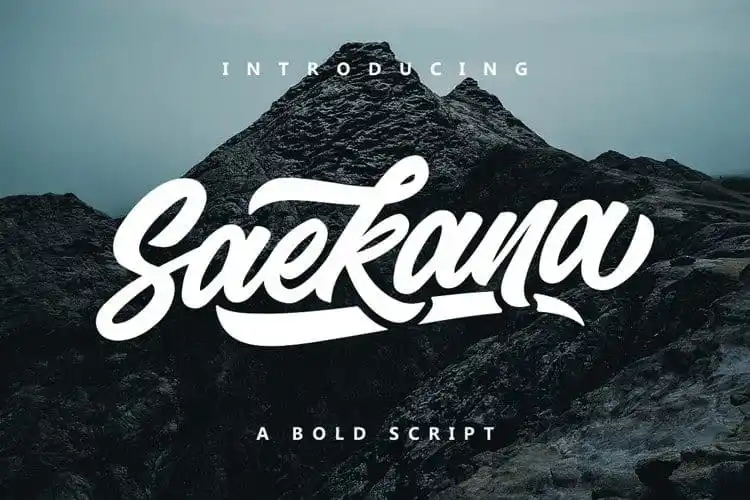
Saekana Bold Script Font – Fonte Grátis
Saekana Bold Script Font
Saekana Bold Script Font é uma tipografia script agradável que se destaca por sua textura grossa e elegante. Esta fonte oferece uma aparência imponente, perfeita para uso em logotipos, cabeçalhos de websites, design de moda e cartões de casamento. Suas linhas sólidas e curvas delicadas combinam perfeitamente para criar um efeito atraente e sofisticado. Ideal tanto para projetos criativos quanto para elementos mais formais, Saekana é uma escolha inteligente para quem procura uma fonte script poderosa e sedutora. Seja em um design de website elegante ou no rótulo de sua marca, ela está sempre em sintonia com as tendências atuais.